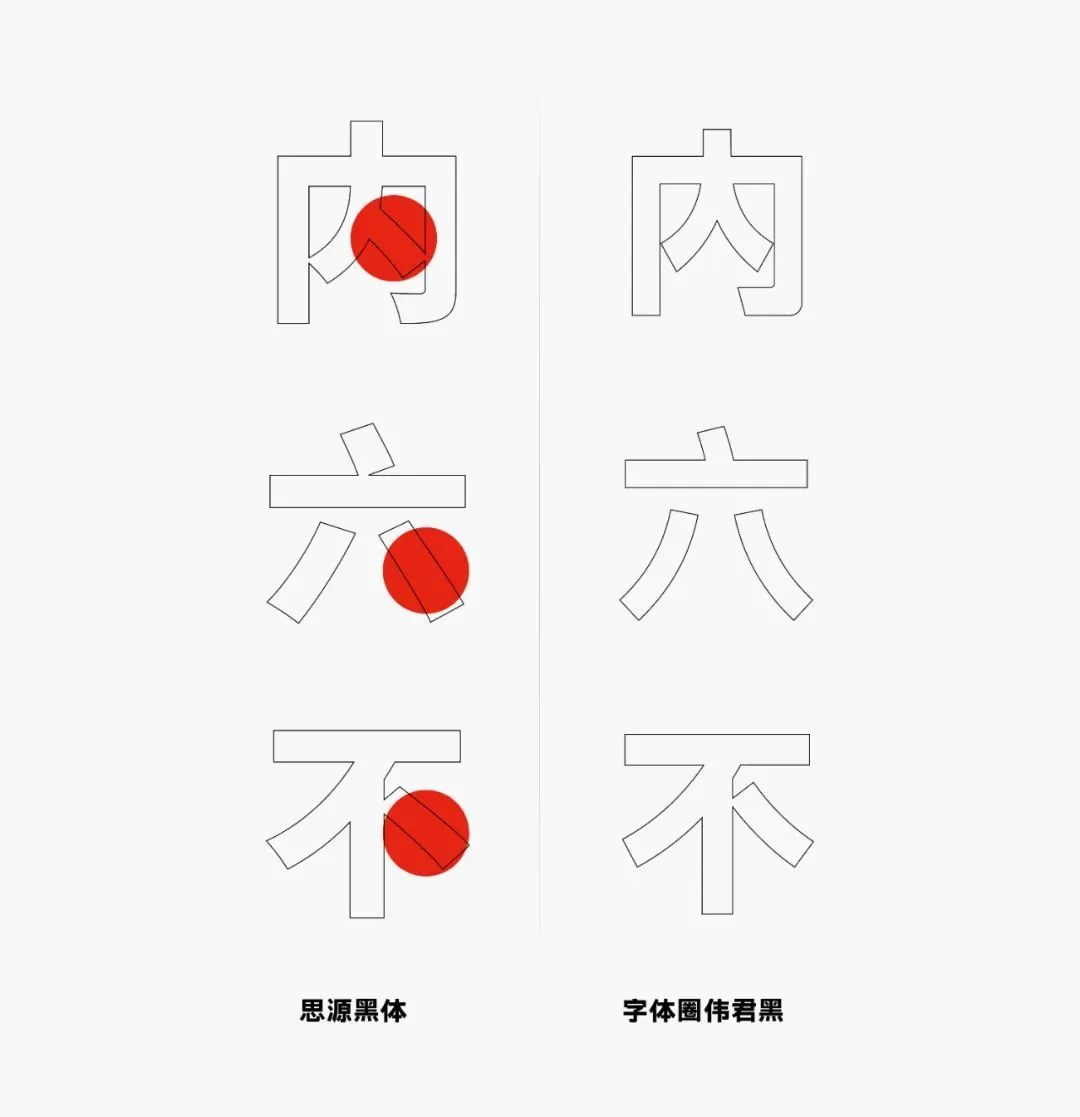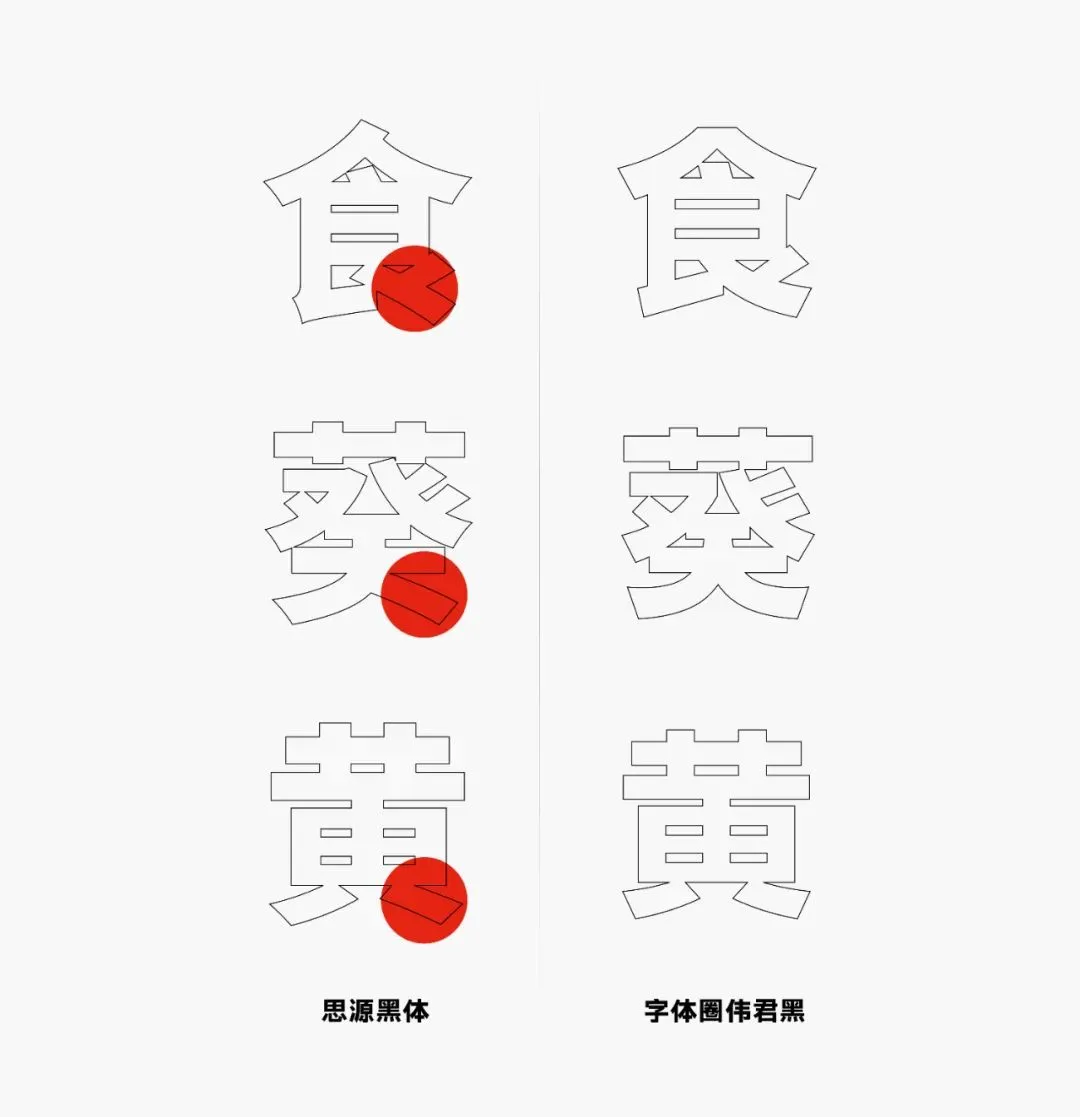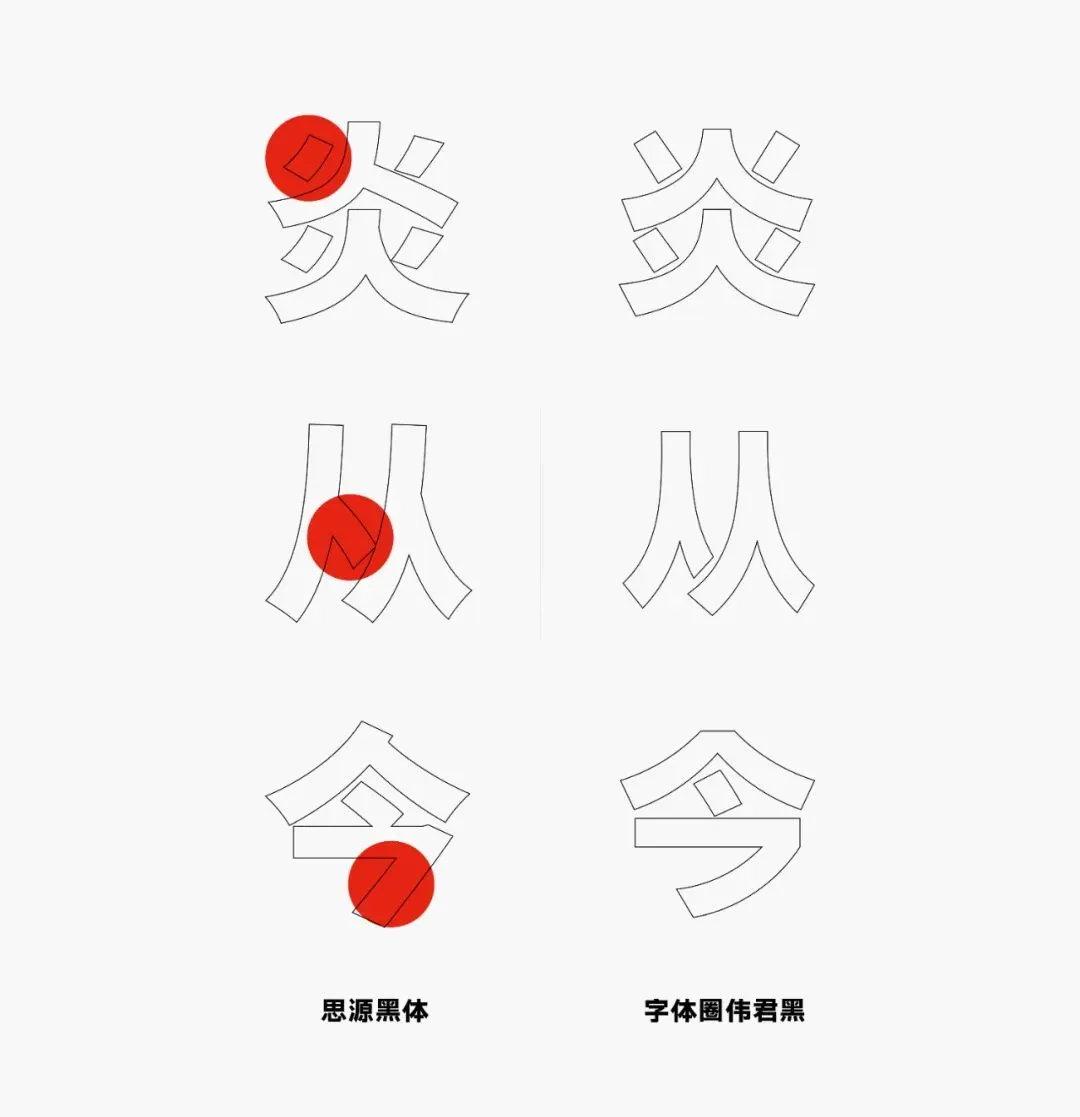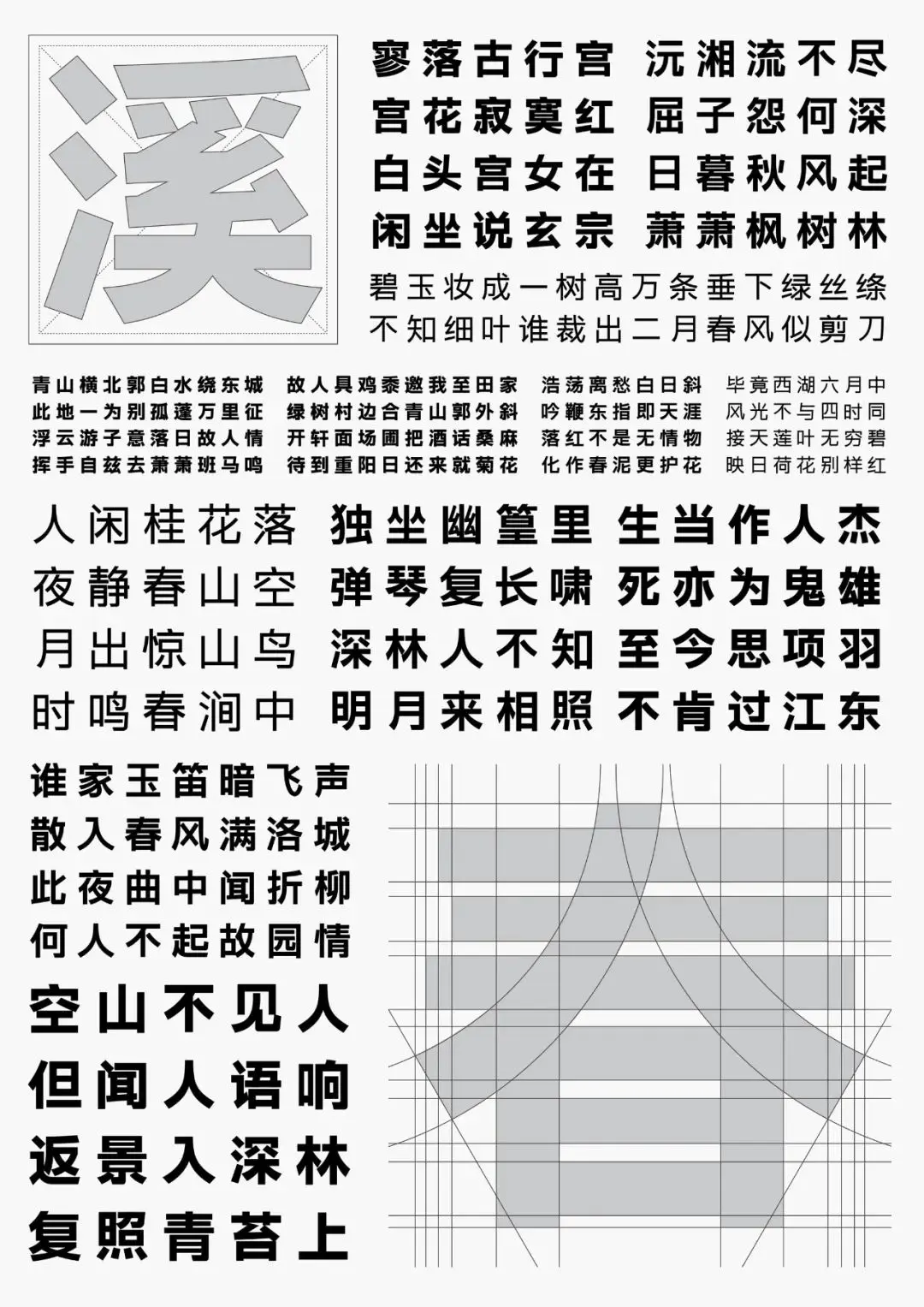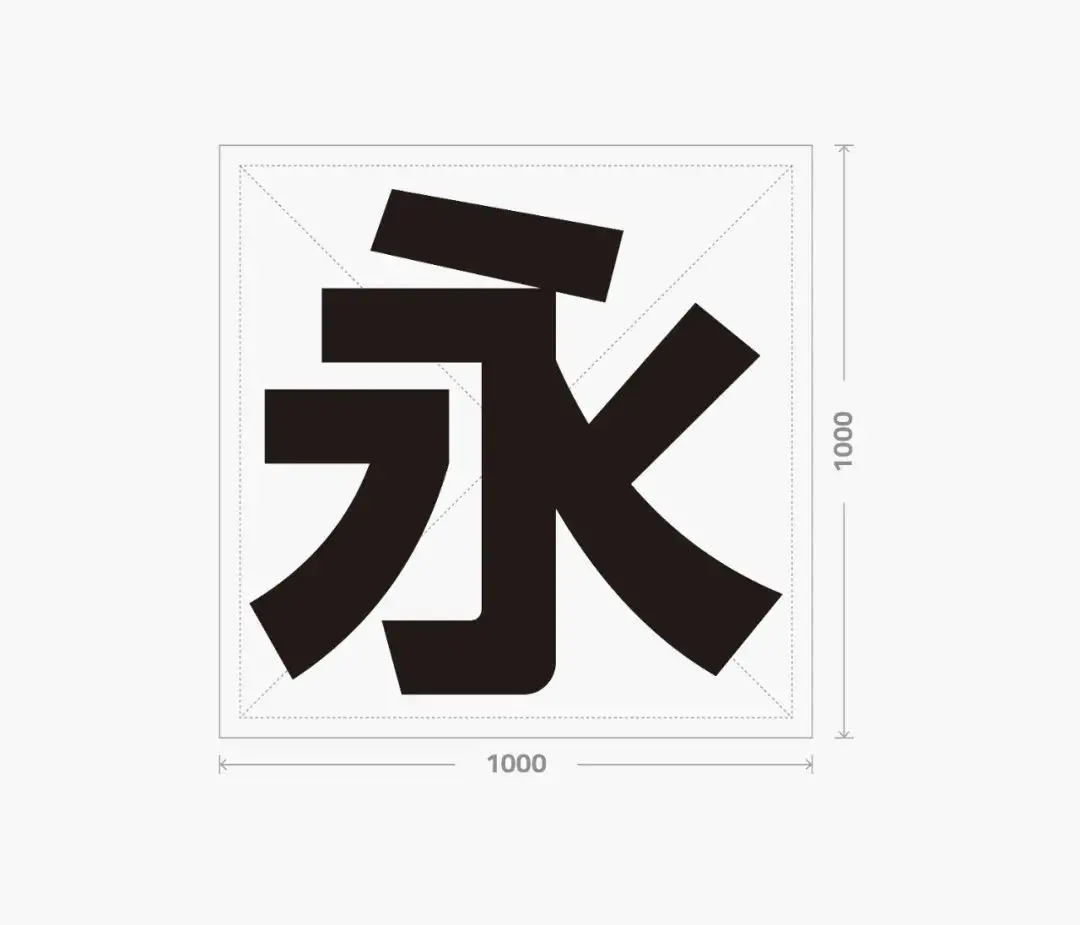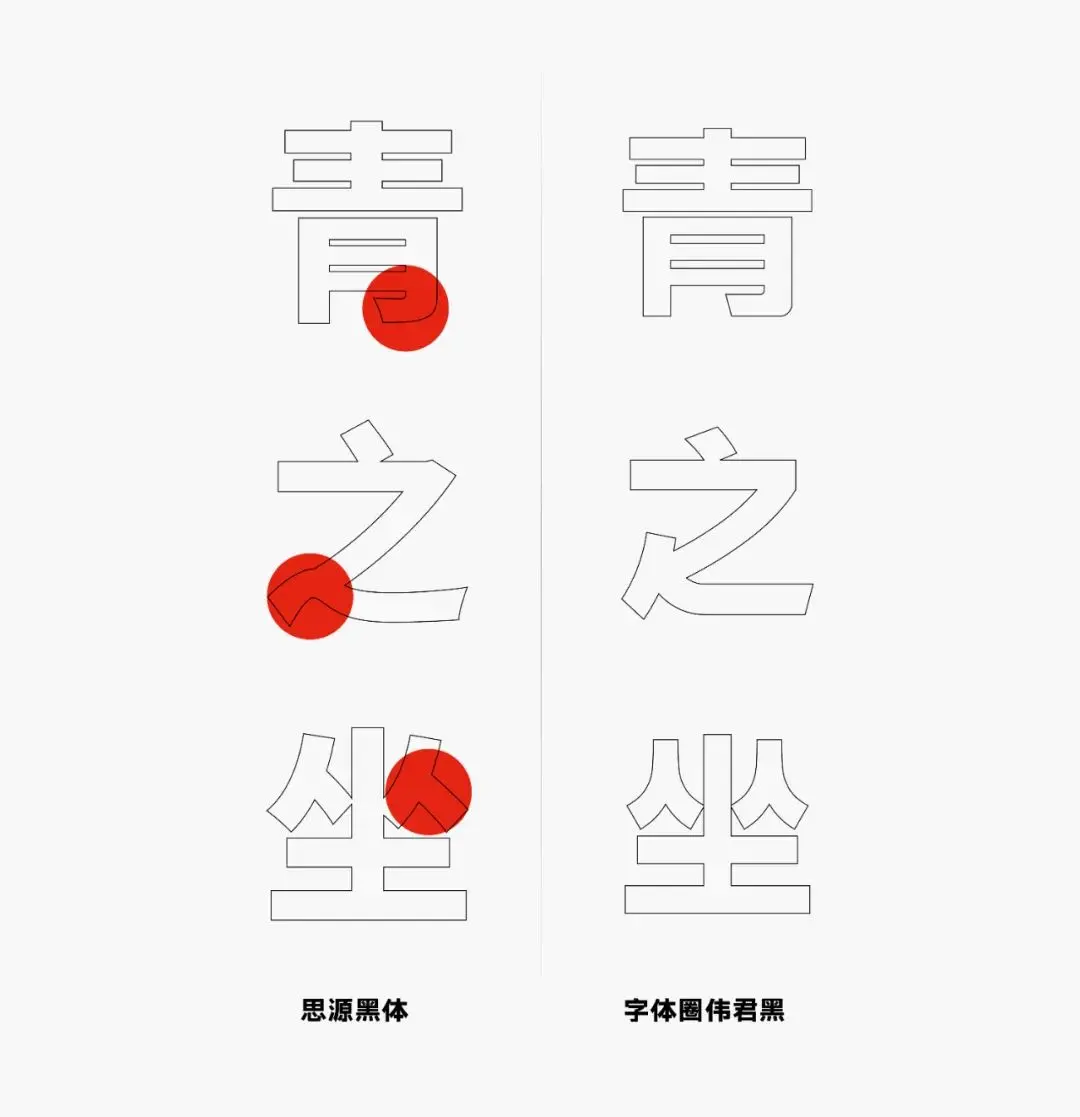
字體圈偉君黑預覽
字體圈偉君黑介紹
字體圈偉君黑這套字體分別有W1、W2、W3三個字重,適合多場景使用,例如正文排版、標題設計等,基本能用到字體的地方,都可以使用我們的《字體圈偉君黑》,字庫現包含6763個漢字及若干個符號等,總字符7000餘。
字體作者:蔡偉君 偉君黑設計師
蔡偉君,從事設計行業十餘年,目前就職於深圳一家IT公司設計總監,有豐富的設計實踐經驗,曾服務過一些大型企業業務,諸如騰訊、OPPO、北汽、新疆農信等設計項目。
作者的話:我從事設計工作十多年,也從一個懵懂少年變為一位不惑大叔。2020年初,開始爆發疫情,公司放假,上班時間需要等通知,在家呆了一個多月,早上起來就無事可做的日子真的很難熬,回想自己設計生涯這些年,真是平平庸庸,碌碌無為,不曾做過一件有意義的事情,心中有些慚愧與落寞。
人好不容易來到這星球一趟,總該留下點甚麼吧,字體設計是我比較感興趣和稍微擅長的事情,所以我想盡自己一點力,在這星球短暫的旅行留下點紀念。後來我看到鄒老師發佈的“字體圈欣意冠黑體”,並找到了聯繫方式,並表達了我想做一款免費字體的意願,這就是我設計這款字體的心路歷程。
我的話:蔡老師的想法其實跟我或者跟很多字體設計師是同樣的想法,希望留下點東西在這個世界上,其他設計作品隨著時間也許有一天終將會消失,但是字體是可以延續的。《字體圈偉君黑》可以說是我一點點看著做完的,我本身對正文黑體的研究不是很深,也不敢輕易去做,所以這個字體我基本沒有給蔡老師很多的修改意見。
其實最開始的時候,蔡老師說很喜歡森澤黑體,想要參照森澤黑體做一款黑體字,我表示市面上的免費商用的黑體字已經很多了,可能做出來了使用者不多,沒甚麼市場,但是蔡老師表示很喜歡森澤的筆形,對黑體字研究頗深,堅持想要做一款黑體字,最後我還是答應了,前前後後花了將近兩年時間。花兩年時間做一款意料不到將來的免費字體,不得不說蔡老師真的很喜歡字體,也真的很偉大。